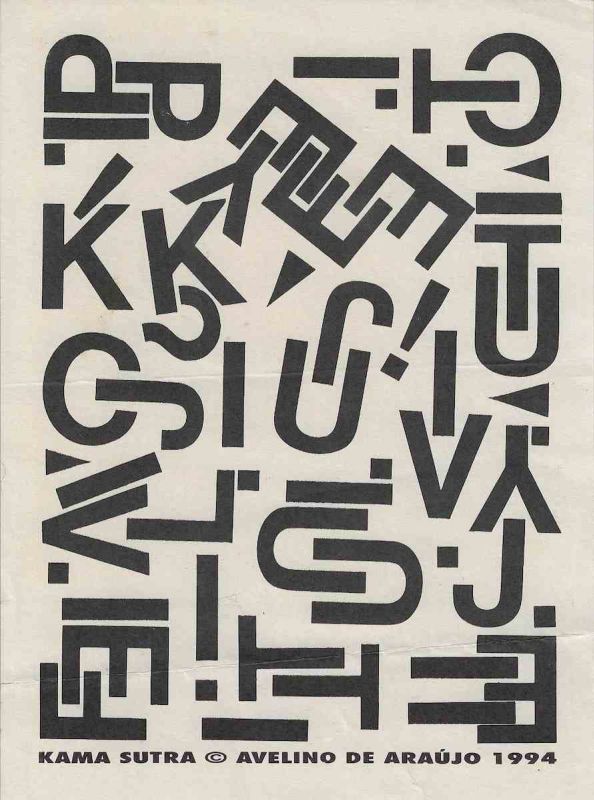
Kama Sutra Pequeno é uma impressão gráfica de Avelino de Araújo realizada em 1994, vinculada à poesia visual, à poesia experimental, à arte conceitual, à tipografia e às investigações intersígnicas relacionadas ao campo do Poema Processo.
Kama Sutra Pequeno é uma impressão gráfica de Avelino de Araújo realizada em 1994, vinculada à poesia visual, à poesia experimental, à arte conceitual, à tipografia e às investigações intersígnicas relacionadas ao campo do Poema Processo. A composição apresenta uma grande concentração de letras maiúsculas, sinais gráficos, pontos, retângulos, triângulos e fragmentos tipográficos distribuídos por quase toda a superfície da folha. Os caracteres aparecem em diferentes orientações, alguns verticais, outros horizontais, inclinados, invertidos, girados ou parcialmente sobrepostos. O título Kama Sutra orienta a leitura da imagem para o campo do corpo, do erotismo, da sexualidade, do encontro e das múltiplas posições possíveis entre formas. Avelino de Araújo substitui a representação figurativa de corpos humanos por letras e sinais abstratos. Os caracteres passam a atuar como membros, troncos, articulações, movimentos, aproximações e encaixes. A distribuição dos elementos cria uma espécie de coreografia tipográfica em que as letras parecem tocar, cruzar, apoiar, envolver ou penetrar outras formas. O termo Pequeno pode indicar o formato reduzido da peça, uma versão condensada do tema ou uma síntese visual de um repertório corporal muito mais amplo. A obra transforma o alfabeto em corpo e utiliza a geometria das letras para sugerir relações físicas sem recorrer à imagem anatômica direta. As formas curvas podem lembrar abraços, flexões e partes do corpo, enquanto barras, ângulos, pontos e módulos retos sugerem tensões, direções, apoios e movimentos. A ausência de uma ordem linear impede a leitura verbal convencional e estimula uma percepção simultânea da página. O observador percorre a composição em várias direções e constrói associações entre caracteres isolados ou pequenos grupos. Algumas letras permanecem reconhecíveis, mas muitas perdem sua função linguística e passam a operar como matéria visual. A obra explora as relações entre linguagem e desejo, signo e corpo, escrita e gesto, leitura e experiência física. A densidade dos elementos contrasta com o fundo claro e cria uma superfície de intensa atividade gráfica. Kama Sutra Pequeno pode ser compreendida como poema visual, composição tipográfica, mapa corporal, escrita erótica abstrata e documento conceitual. Na parte inferior aparecem a identificação KAMA SUTRA, o símbolo de autoria, o nome Avelino de Araújo e o ano 1994. Palavras chave para indexação: Avelino de Araújo, Kama Sutra Pequeno, Kama Sutra, 1994, impressão gráfica, poesia visual brasileira, poema visual, poesia experimental, arte conceitual, Poema Processo, erotismo, sexualidade, corpo, desejo, posições corporais, tipografia experimental, letras como corpos, composição tipográfica, escrita visual, gesto, movimento, sobreposição, rotação, inversão, palavra imagem, texto imagem, semiótica, intersigno, comunicação visual, arte gráfica brasileira, múltiplo gráfico, arquivo de poesia visual, arte brasileira do século vinte.TEXT FOR THE SALSA PROGRAM IN ENGLISH: Kama Sutra Small is a graphic print by Avelino de Araújo produced in 1994 and associated with visual poetry, experimental poetry, conceptual art, typography and intersemiotic investigations related to the field of the Poema Processo movement. The composition presents a dense concentration of capital letters, graphic signs, dots, rectangles, triangles and typographic fragments distributed across almost the entire surface of the sheet. The characters appear in different orientations, including vertical, horizontal, inclined, inverted, rotated and partially superimposed positions. The title Kama Sutra guides interpretation toward the body, eroticism, sexuality, encounter and the multiple positions that forms may occupy in relation to one another. Avelino de Araújo replaces figurative representations of human bodies with letters and abstract signs. The characters begin to function as limbs, torsos, joints, movements, approaches and connections. Their distribution creates a form of typographic choreography in which letters appear to touch, cross, support, surround or enter other forms. The term Small may indicate the reduced format of the piece, a condensed version of the theme or a visual synthesis of a much broader bodily repertoire. The work transforms the alphabet into a body and uses the geometry of letters to suggest physical relationships without directly representing anatomy. Curved forms may evoke embraces, flexions and parts of the body, while bars, angles, dots and straight modules suggest tension, direction, support and movement. The absence of linear order prevents conventional verbal reading and encourages simultaneous perception of the page. The viewer moves through the composition in several directions and constructs associations among isolated characters or small groups. Some letters remain recognizable, while many lose their linguistic function and operate primarily as visual matter. The work explores relationships between language and desire, sign and body, writing and gesture, reading and physical experience. The density of the elements contrasts with the light background and creates a surface of intense graphic activity. Kama Sutra Small may be understood as a visual poem, typographic composition, bodily map, abstract erotic writing and conceptual document. The lower section contains the identification KAMA SUTRA, the authorship symbol, the name Avelino de Araújo and the year 1994. Keywords for indexing: Avelino de Araújo, Kama Sutra Small, Kama Sutra, 1994, graphic print, Brazilian visual poetry, visual poem, experimental poetry, conceptual art, Poema Processo, eroticism, sexuality, body, desire, bodily positions, experimental typography, letters as bodies, typographic composition, visual writing, gesture, movement, superimposition, rotation, inversion, word image, text image, semiotics, intersign, visual communication, Brazilian graphic art, graphic multiple, visual poetry archive, twentieth century Brazilian art.
Impressão gráfica em tinta preta sobre papel claro de tonalidade levemente amarelada. A composição ocupa quase toda a área central da folha e apresenta grande quantidade de caracteres tipográficos e sinais distribuídos de maneira irregular. Observam se letras maiúsculas como A, C, E, F, G, I, J, K, L, P, S, T, U, V e Y, além de pontos, barras, pequenos quadrados, triângulos e segmentos retangulares. Os caracteres variam de tamanho, espessura e orientação. Muitos aparecem girados, invertidos, inclinados ou unidos a outros elementos, formando estruturas visuais que podem sugerir corpos em movimento e diferentes relações espaciais. Algumas áreas apresentam maior concentração e sobreposição, enquanto outras preservam intervalos claros entre as formas. A composição possui forte contraste, elevada densidade visual e leitura multidirecional. Na parte inferior encontra se a inscrição KAMA SUTRA, seguida pelo símbolo de autoria, pelo nome AVELINO DE ARAÚJO e pelo ano 1994. O suporte apresenta ondulações, vincos, marcas de dobra, pequenas manchas, alterações de tonalidade e sinais de envelhecimento e manuseio. A peça pode ser classificada como poema visual, impressão de artista, múltiplo gráfico, estudo tipográfico, composição erótica abstrata e documento conceitual, sendo relevante para pesquisas sobre Avelino de Araújo, Poema Processo, poesia visual, corpo, sexualidade, erotismo, tipografia, semiótica e produção gráfica brasileira.OBSERVATION TEXT IN ENGLISH: Graphic print in black ink on light colored paper with a slightly yellowed tone. The composition occupies almost the entire central area of the sheet and contains a large number of typographic characters and signs distributed irregularly. Capital letters such as A, C, E, F, G, I, J, K, L, P, S, T, U, V and Y are visible, together with dots, bars, small squares, triangles and rectangular segments. The characters vary in size, thickness and orientation. Many appear rotated, inverted, inclined or joined to other elements, forming visual structures that may suggest bodies in motion and different spatial relationships. Some areas present greater concentration and superimposition, while others preserve light intervals between forms. The composition has strong contrast, high visual density and multidirectional reading. The lower section contains the inscription KAMA SUTRA, followed by the authorship symbol, the name AVELINO DE ARAÚJO and the year 1994. The support presents undulations, creases, fold marks, small stains, changes in tone and signs of aging and handling. The piece may be classified as a visual poem, artist print, graphic multiple, typographic study, abstract erotic composition and conceptual document, making it relevant to research on Avelino de Araújo, Poema Processo, visual poetry, the body, sexuality, eroticism, typography, semiotics and Brazilian graphic production.
Kama Sutra Small is a graphic print by Avelino de Araújo produced in 1994 and associated with visual poetry, experimental poetry, conceptual art, typography and intersemiotic investigations related to the field of the Poema Processo movement.